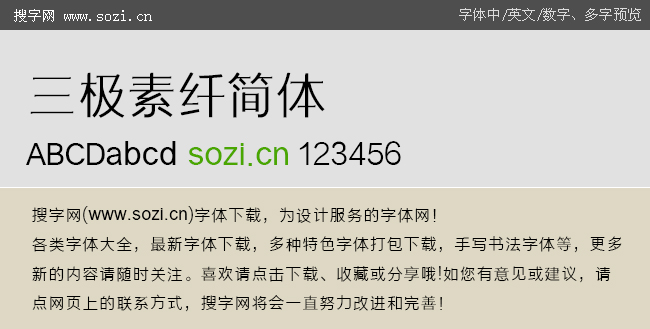
三極素纖簡體
搜字網(wǎng)給大家提供一款三極素纖簡體中文字體下載,三極素纖簡體字體是由三極字庫出品的一款中文簡體字體,該字體橫豎勾帶有宋體結(jié)構(gòu),其字形清新,結(jié)構(gòu)嚴(yán)謹,布白均勻,結(jié)合了宋體飽滿的結(jié)構(gòu)特征,又不失黑體本身的銳利簡潔。適用于平面宣傳設(shè)計、網(wǎng)頁設(shè)計、海報設(shè)計等應(yīng)用。